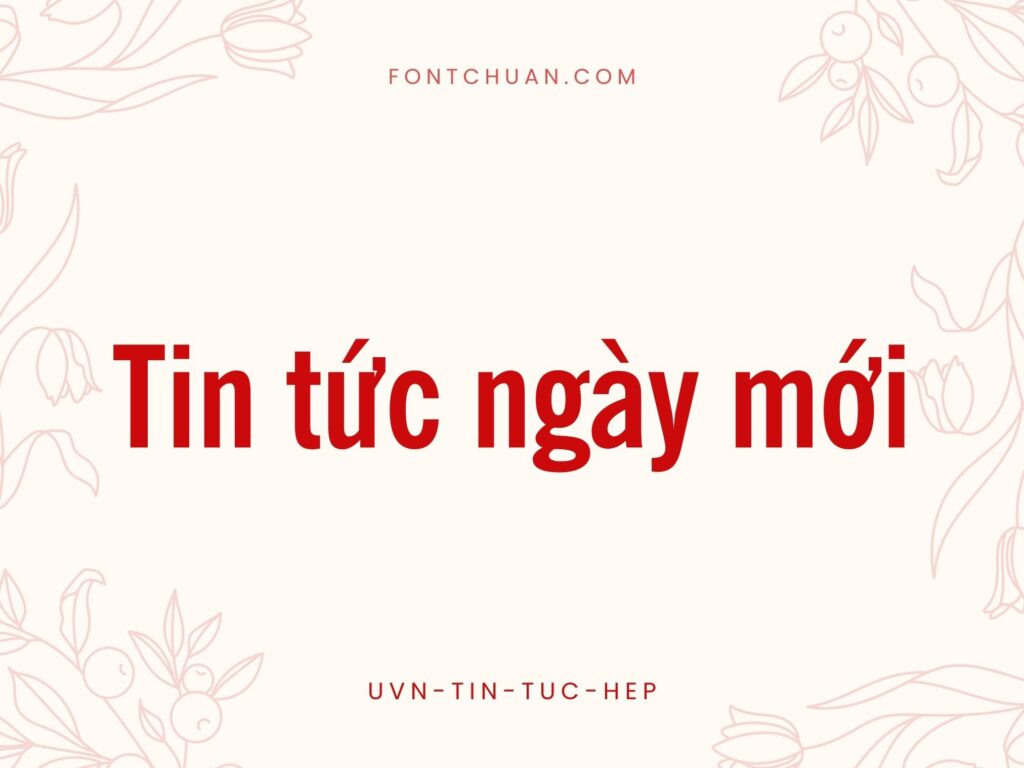
Font UVN Tin Tuc Hep Việt Hóa
UVN Tin Tức Hẹp là biến thể condensed (thu hẹp chiều ngang) của dòng font UVN Tin Tức, mang đến cảm giác gọn gàng, tiết kiệm không gian nhưng vẫn giữ được sự rõ ràng và hiện đại vốn có của kiểu chữ sans-serif. Font được tối ưu hóa cho các thiết kế cần hiển thị nhiều nội dung trong diện tích nhỏ mà vẫn đảm bảo tính thẩm mỹ và dễ đọc. Khi kết hợp cùng Font Monospace, UVN Tin Tức Hẹp có thể tạo nên sự cân bằng thú vị giữa phong cách truyền thông hiện đại và tính kỹ thuật chuẩn xác, giúp thiết kế đa dạng hơn trong nhiều ngữ cảnh khác nhau. Font này chỉ được sưu tầm và đăng bởi thành viên của Font Chuẩn, góp phần làm phong phú kho tàng font Việt hóa ứng dụng cao cho người dùng sáng tạo nội dung và thiết kế chuyên nghiệp.
Với cấu trúc ký tự hẹp nhưng vẫn thoáng đãng, UVN Tin Tức Hẹp lý tưởng cho thiết kế poster, tiêu đề cột báo, giao diện app hoặc tài liệu kỹ thuật. Font có độ đậm vừa phải, phù hợp khi cần tạo điểm nhấn mà không gây rối mắt. Các ứng dụng phù hợp gồm tạp chí, banner quảng cáo, website tin tức. Ngành nghề phù hợp bao gồm công nghệ, giáo dục, quảng cáo và bất động sản. Font cũng phù hợp với các sự kiện như Tết, ngày Nhà giáo, sinh nhật hoặc lễ hội nhờ phong cách truyền thông hiện đại mà font thể hiện.